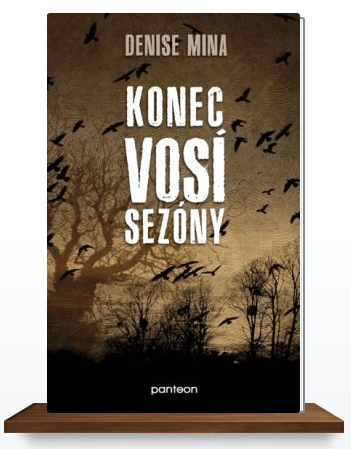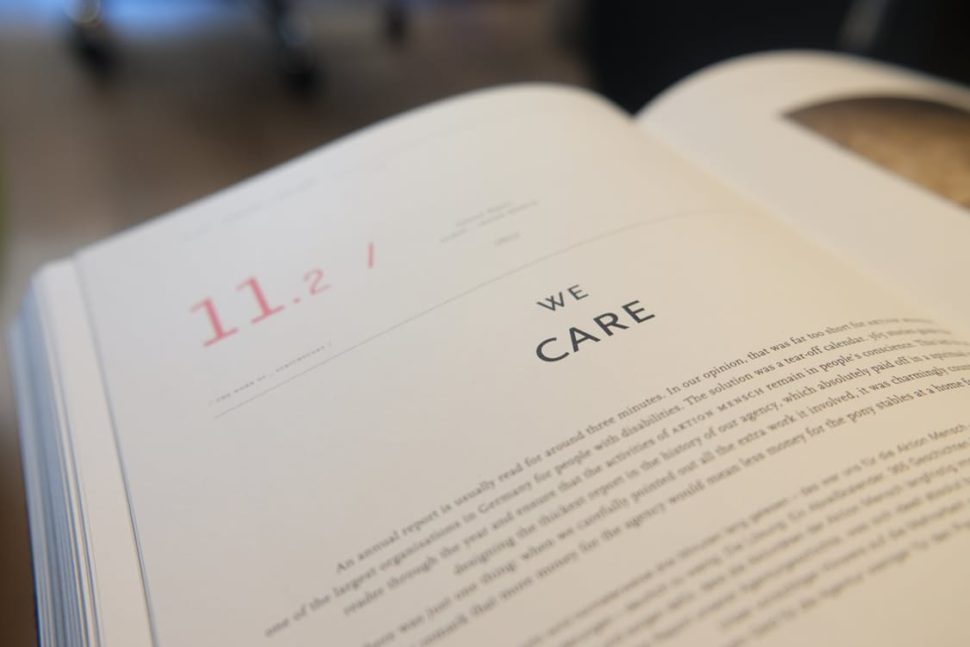
Jste hrdým autorem knihy.
Zatím je pouze ve vaší mysli, skládají se vám kapitoly a možná už jsou i zaznamenané ve Wordu. Ani se vám tomu nechce věřit, že byste už za chvíli mohli ve společnosti jen tak nonšalantně prohodit :“ Ve své první knize jsem napsal(a)…“, ale už brzy to bude realita.
Zbývá už jen velmi málo a budete ji držet v ruce. Vonící tiskárnou a papírem. Daleko převyšující všechny e-booky a e-knihy. Protože v tom éčku si neodvezete zrnka písku z pláže, nebo s ním nepodložíte nohu od stolu.
Obsah knihy je plně ve vaší režii a nepochybuji, že skvělý,  ale musíte ho umět i prodat. A jedním z důležitých „prodejců“ je font. Pojďte se podívat, jak taková drobnost jako je výběr písma může vaši knihu potopit anebo vyzdvihnout.
Jedna z prvních a základních otázek, kterou si musíte položit, pokud budete sami tvořit design vaší knihy, je: Jaký použiju font?
Joel Friedlander, book designer
Věřím tomu, že jako autor knihy si pokládáte daleko víc otázek, dokonce bych řekla, že z těch otázek, odpovědí a „TO DO listů“ nemůžete až do vydání knihy spát. Ale tato je fakt důležitá, i když se vám to nezdá a máte jí v seznamu někde na posledním místě.
Proč vás má taková maličkost, jako je FONT zajímat?
Přečtete si následující větu pomalu a několikrát, protože to je alfa a omega tohoto článku.
[box background=#cfc090 color=#010010]Protože VAŠÍ KNIHU (pokud to není netrpělivě očekávaný bestseller typu Harry Potter X.díl) si lidé NEKOUPÍ, pokud je obálka nezaujme, zmate, odradí a nebo JI ODLOŽÍ nedočtenou, když se jim bude špatně číst.[/box]
A za to vše je zodpovědný font. Samozřejmě, ruku v ruce s kompletní typografickou a grafickou úpravou.
Kdy si knihu lidé nekoupí?
Když je nezaujme. Tečka. Teda, možná fungují tamtamy a kladné reference a je skupina lidí, která zamíří přímo k poličce, na které je vystavená a vezmou si ji, i když bude obálka z balicího papíru nadepsaná ručně. Ale předpokládám, že cílíte i na lidi, kteří o vás nikdy neslyšeli. Nebo slyšeli, ale neví úplně přesně, co čekat. A tady je médium, které jim tuto informace (co od vás čekat) zprostředkuje. Jmenuje se:
OBÁLKA
Obálka knihy má vyjadřovat esenci knihy. Podíváte se na ni a je vám vše jasné. Klid, stres, drama, romantika… ale někdy evokuje jen nudu a zmatek. Nudu, když je kýčovitá, obyčejná, bez nápadu. A zmatek, když spolu jednotlivé části obalu neladí.
Co jsou to ty jednotlivé části?
Každá tato část mluví jasnou řečí k podvědomí čtenářů a vypráví jim příběh, který v knize najdou. A je na vás, abyste vybrali takové, kteří mluví stejnou řečí.
Prostě když potřebujete knihu o tom, jak uklidit v duchu minimalismu, pohledem ani nezavadíte o divoké barvy a rozhárané fonty.
Ale hledáte bílou, jednoduchou kompozici a uspořádaný font. Jinak neuvěříte. Fonty a ilustrace tuto neverbální komunikaci vědomě dotváří. Chcete předávat naději? Nepoužijete černou a font DJ Gross.
Patky, nepatky, tady hledáte písmo, které bude vyjadřovat přesně tu emoci, kterou předáváte knihou.
Kdy se kniha bude špatně číst?
Samozřejmě, když bude jakékoli písmo příliš malé, velké, tenké, tlusté… Ale mimo to i když vyberete nevhodný font. Nejde o to, jestli bude hezký, ale o to, jestli čtenář nebude mít chuť po pěti minutách knihu zaklapnout. A nebude to z jeho strany nezájem o obsah, ale podvědomá reakce mozku „je mi to nepohodlné, moc se při čtení namáhám“.
Kniha nemá text ve sloupcích jako noviny a není to ani e-book, ve kterém máte velkým písmem pár řádků a hromadu obrázků.
Má svá specifika a vyplatí se na ně myslet.
Například většina knih má dlouhé odstavce, zarovnané do bloků. To je velký rozdíl v porovnání s textem, na který jste zvyklí v e-boocích, na webech nebo třeba na plakátech. Patkové písmo, které fungovalo velmi dobře od vynálezu Guttenberga, má v knize své opodstatnění – právě v takovýchto dlouhých pasážích textu vedly patky pohled čtenáře, aby se neztratil a oko neunavilo.
Dnešní doba není pro knihy jednoduchá.
Po staletí respektovala sazba knihy určitá pravidla, která jsou nyní s nástupem digitální éry, a s možností vydání knihy téměř kýmkoli z nás, zpochybňována.
Na rozdíl od textů v online světě se v knize se nesnažíte čtenáře rychle zaujmout a vzbudit jeho pozornost klíčovými slovy či myšlenkami. V knize je stejně důležité každé slovo, věta, odstavec i kapitola. A aby dlouhé bloky textu neunavovaly nejen oči čtenáře, ale i jeho mozek, dejte si práci s výběrem písma, které je pro dlouhé texty určené.
Takže pokud si nezaplatíte grafika, nebo designera, který zná typografická pravidla a specifika knih a rozhodnete se upravit knihu k tisku sami, určitě se vám budou hodit podrobnější informace ke kapitolám:
1/ Kniha není e-book
Jaké jsou rozdíly mezi výběrem fontu pro e-book a pro knihu.
2/ Aby se kniha dobře četla
Jaká jsou kritéria výběru pro font uvnitř knihy.
3/ Obal prodává
Jak vybírat font na obálku.